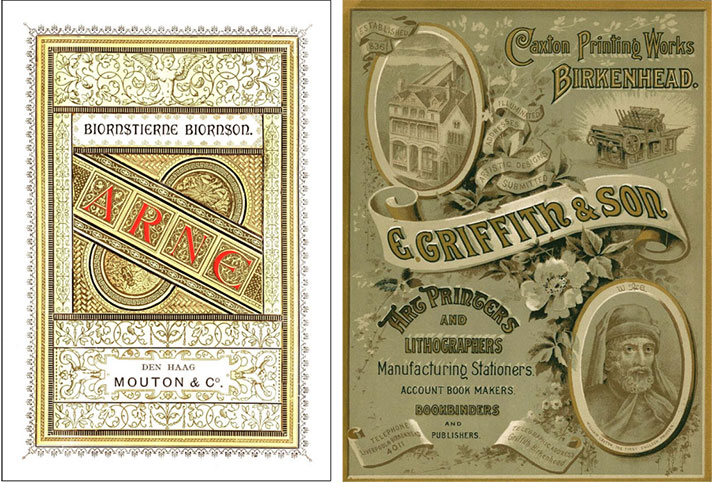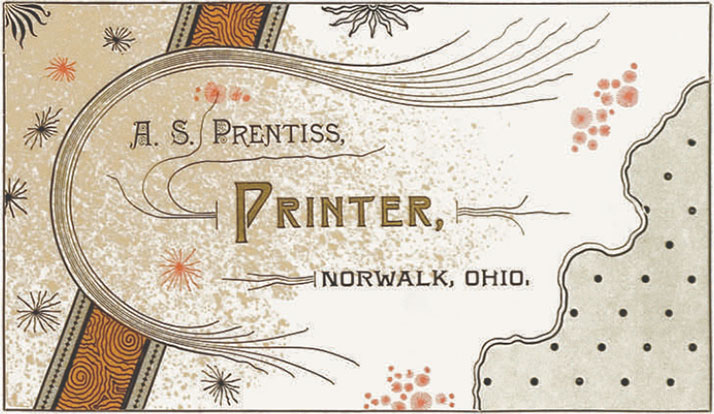
Den ekstravagante, dekorative aksidenstypografien på slutten av 1800-tallet kom til uttrykk ikke minst gjennom internasjonalt organisert byttevirksomhet av arbeidsprøver.
Den første og viktigste av disse var den britiske Printers' International Specimen Exchange (PISE), som kom ut årlig mellom 1880 og 1898.
Denne typografien har lenge vært nedvurdert som overlesset og rotete, og som et uttrykk for forfall og oppløsning av faglige standarder.
Kanskje ser vi nå en økende interesse for og en kritisk anerkjennelse av 1800-talls typografien. Men det har vært vanskelig å skaffe seg et bredt bilde av den.
Amerikaneren Jacob Filipp har nå samlet lenker til alle årgangene av PISE, og samtidig publisert mange eksempler fra utgivelsene. Her kan man på en enkel måte studere det man den gang kalte «satskunst». Han har også postet en svært interessant illustrert analyse av «artistic printing» (som det heter på engelsk).
Eksemplet til venstre vil interessere nordmenn spesielt. Det er et ekstravagant omslag i «den frie retning»s stil, til Bjørnstjerne Bjørnsons Arne, i en nederlandsk utgave. Den inngikk i PISE vol 6, 1885.
I tillegg til den frie retning, er mange av arbeidene historistiske, ved at de tar i bruk elementer typisk for tidligere stilretninger, i særlig grad renessansen.
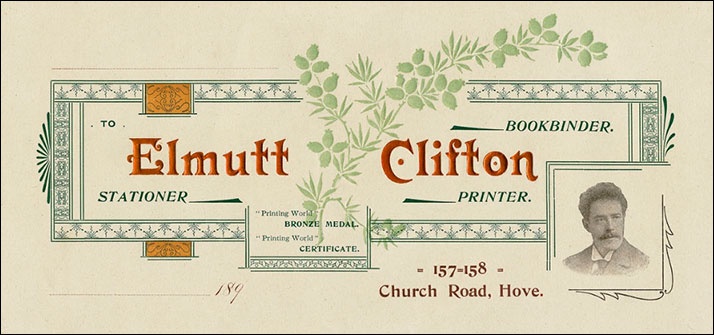
Jeg har en forkjærlighet for denne «viktoriatidas» typografi, og har skrevet en bok om temaet. Her viser jeg alle de kjente norske bidragene i PISE.
ENGLISH SUMMARY
A few words about, and links to, the website of an American typography aficionado. As an admirer of the artistic ‘Victoria’ typography of the 1880s and 1890s, I welcome the efforts of other enthusiasts who spread information about this neglected period in the history of printing.